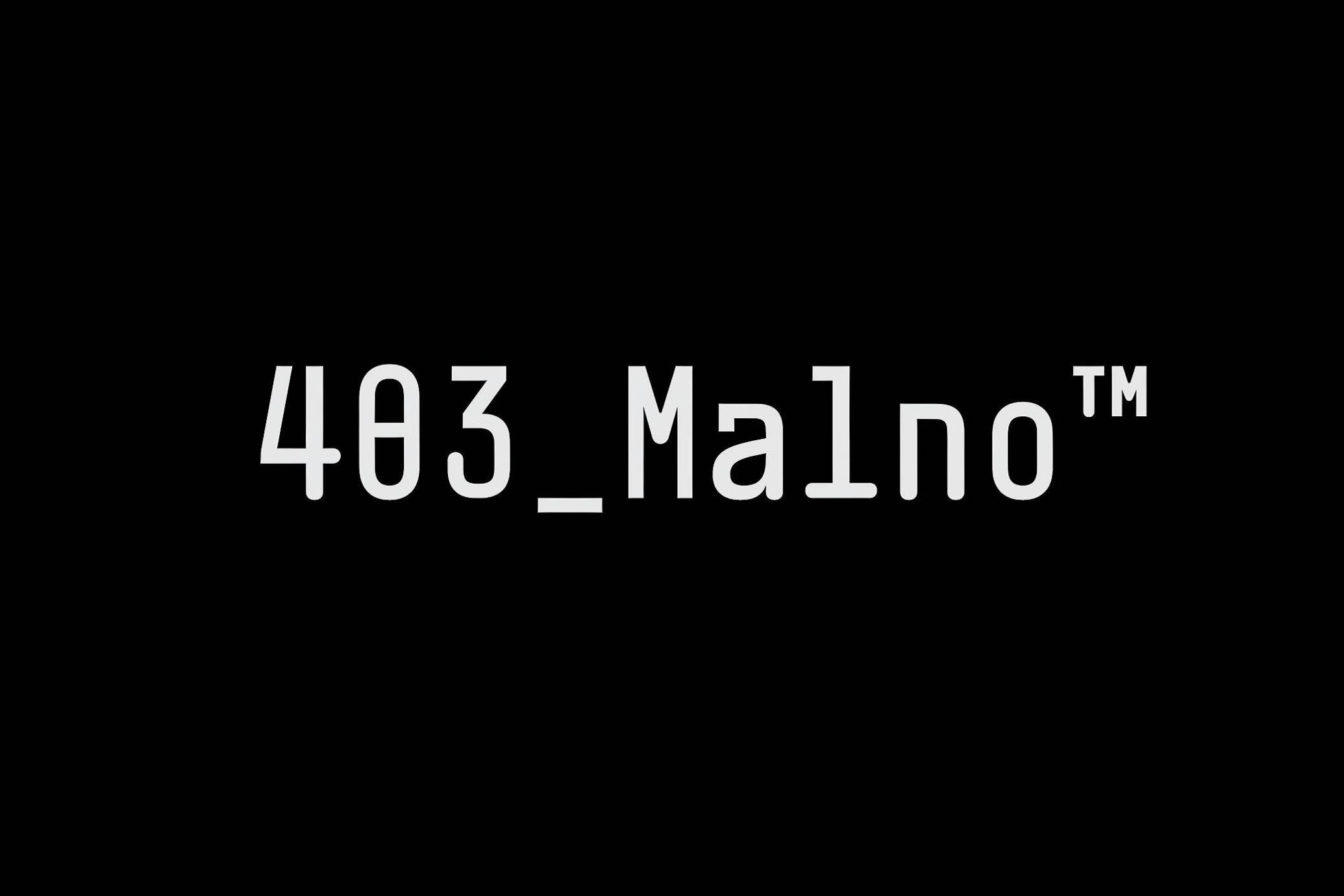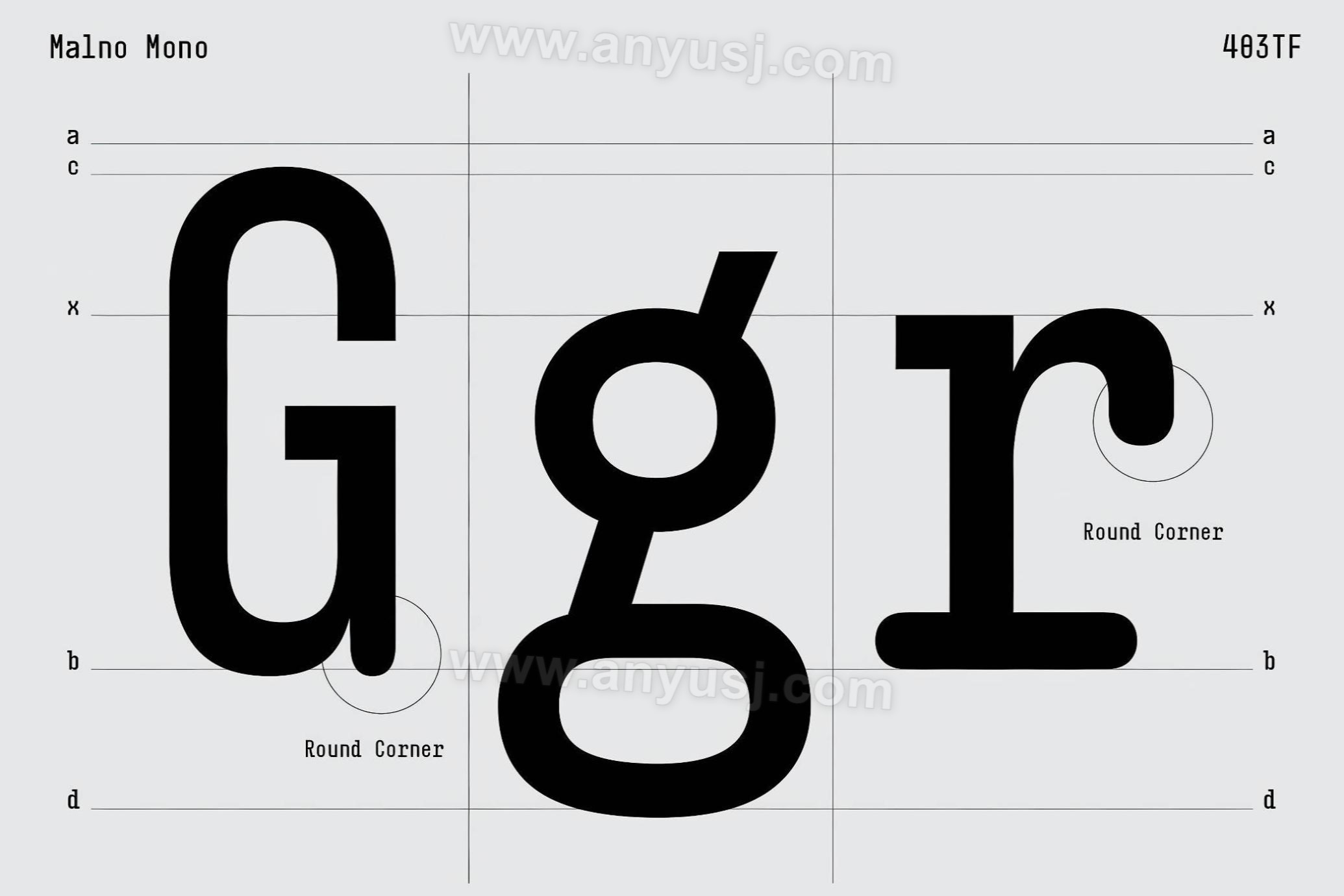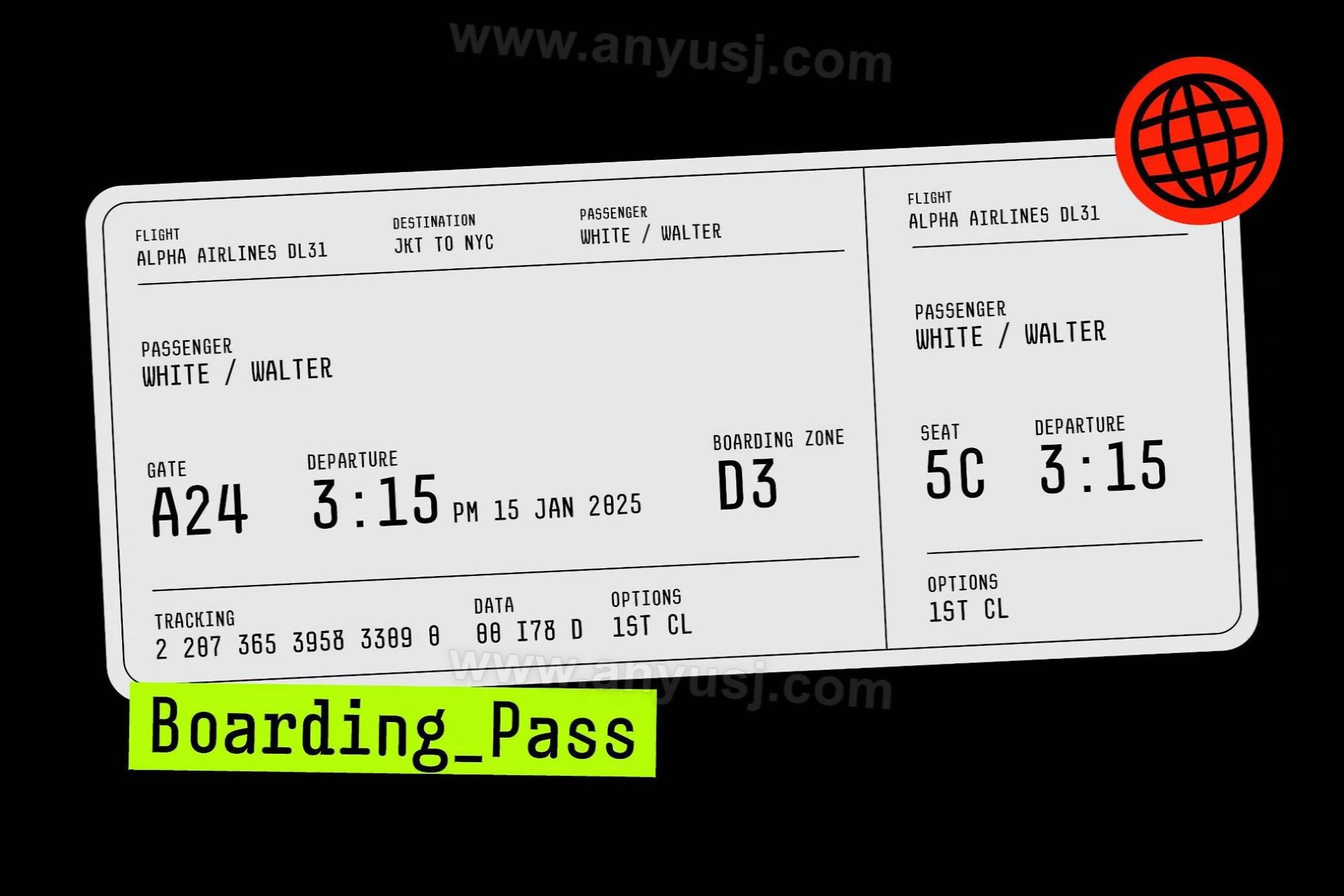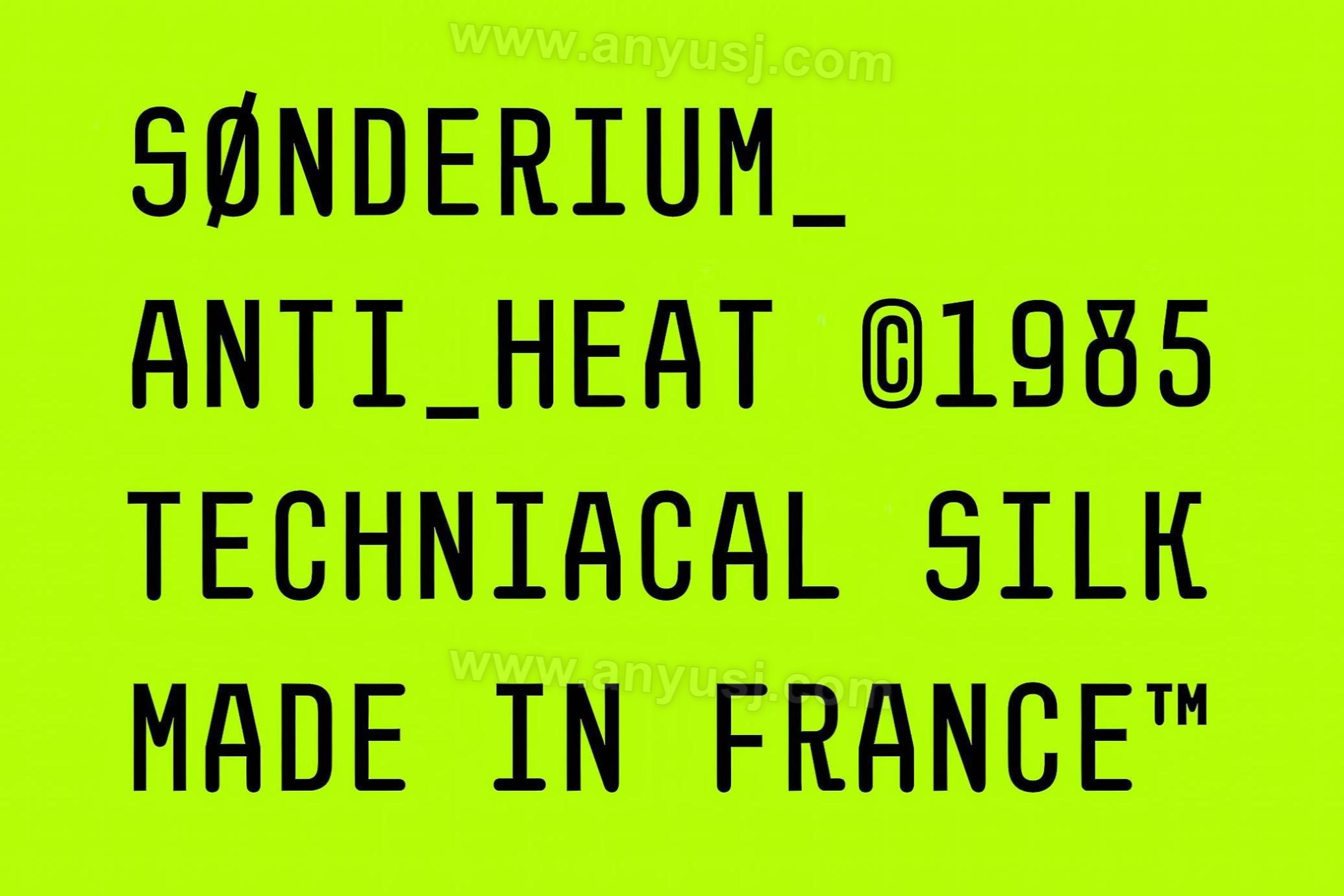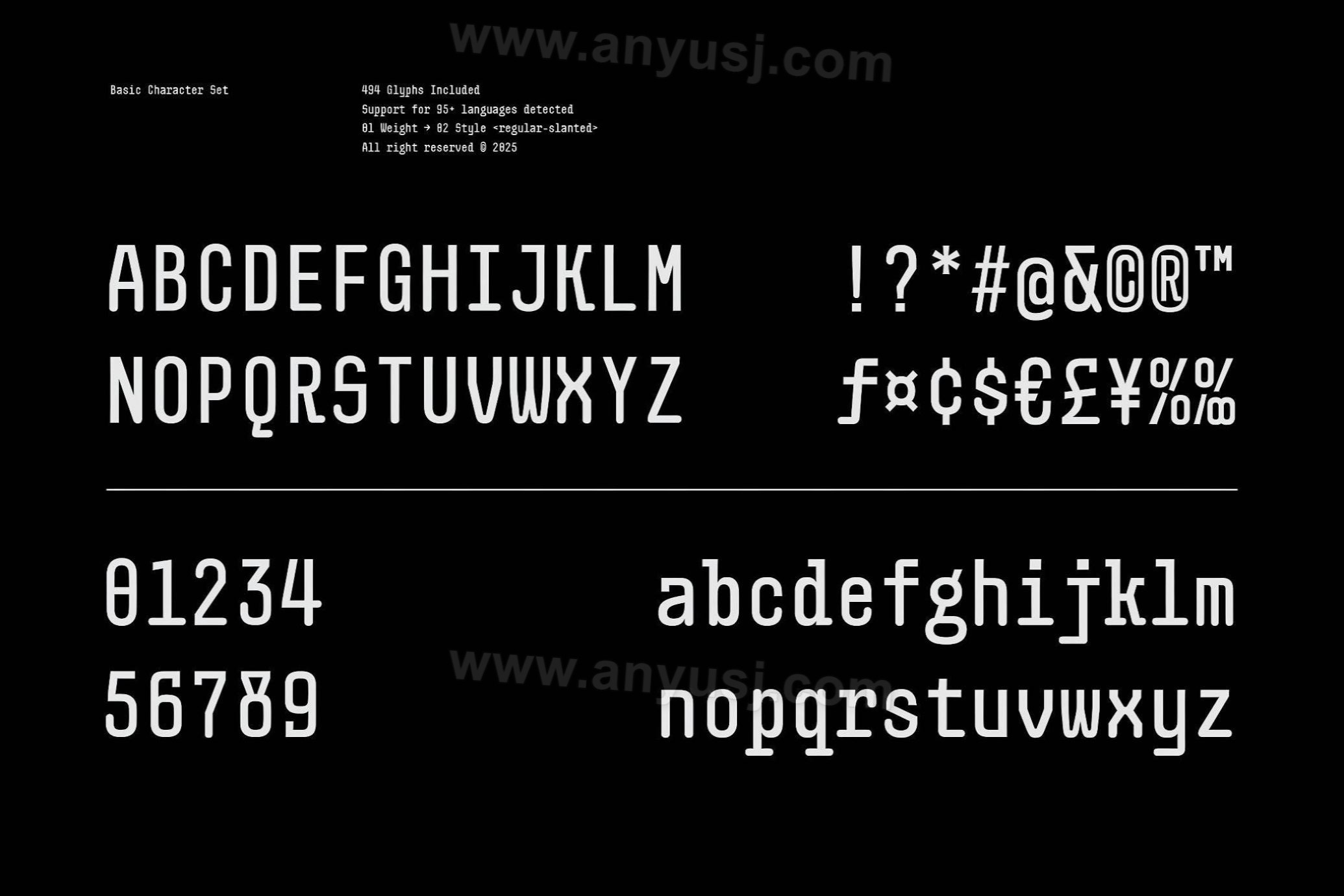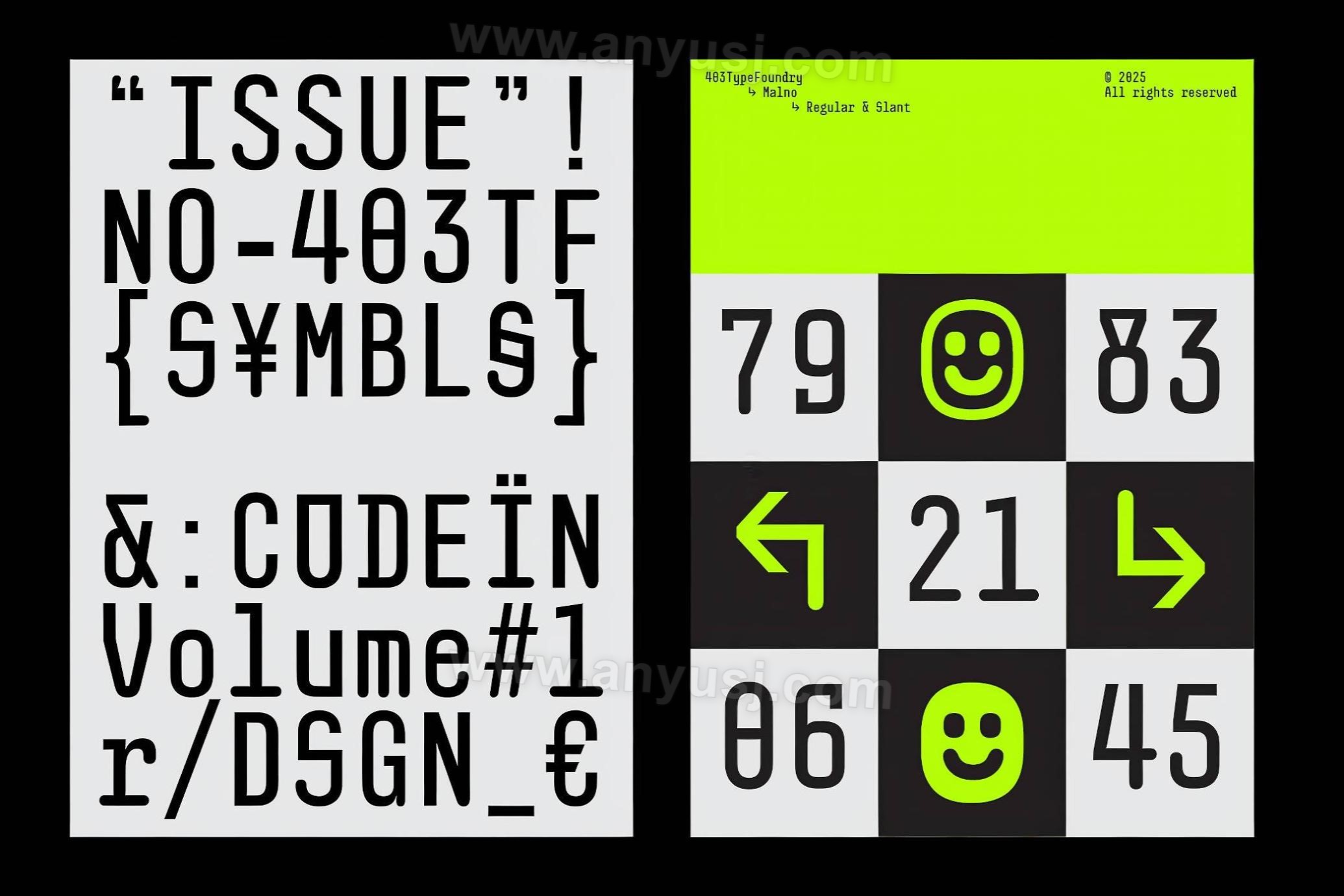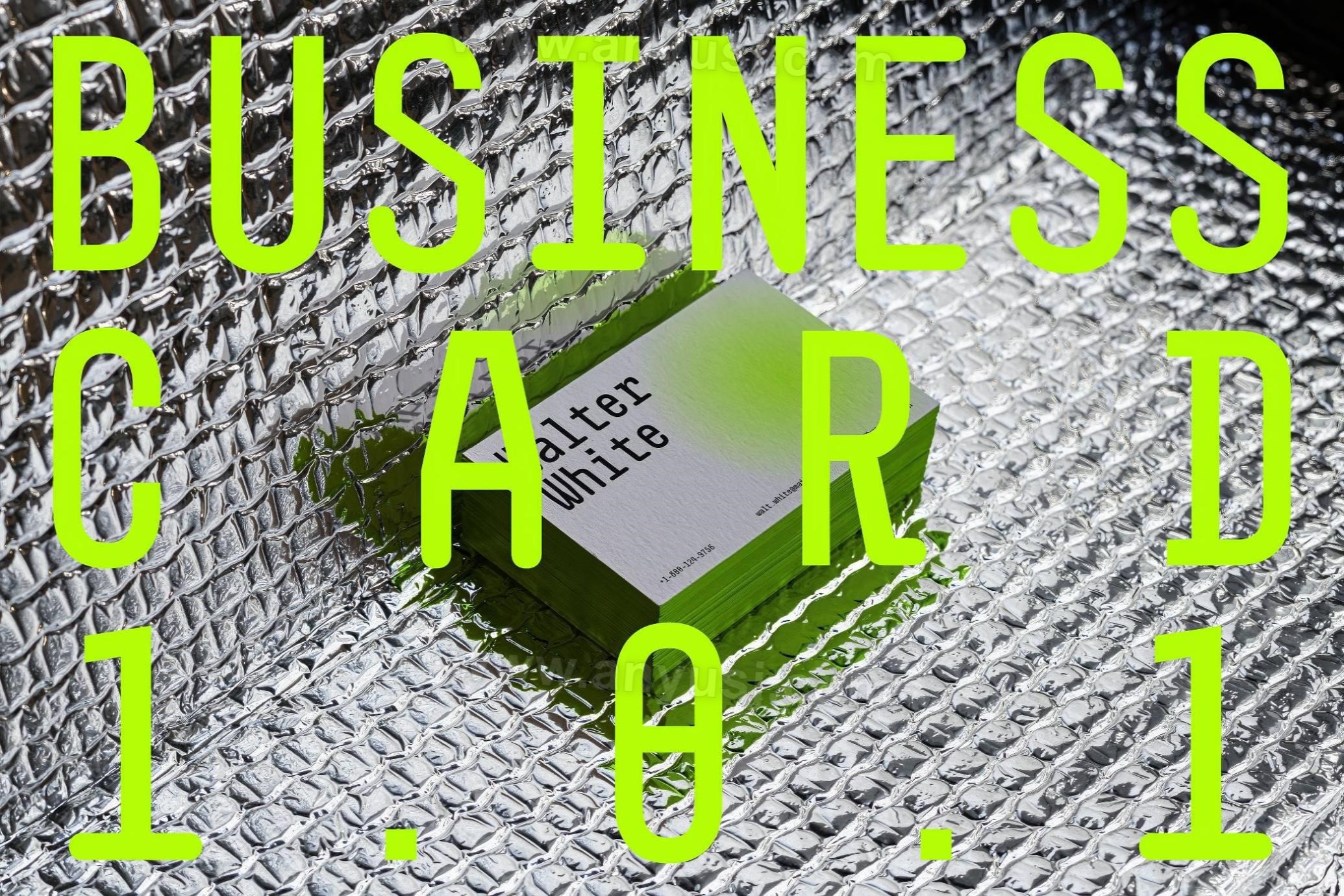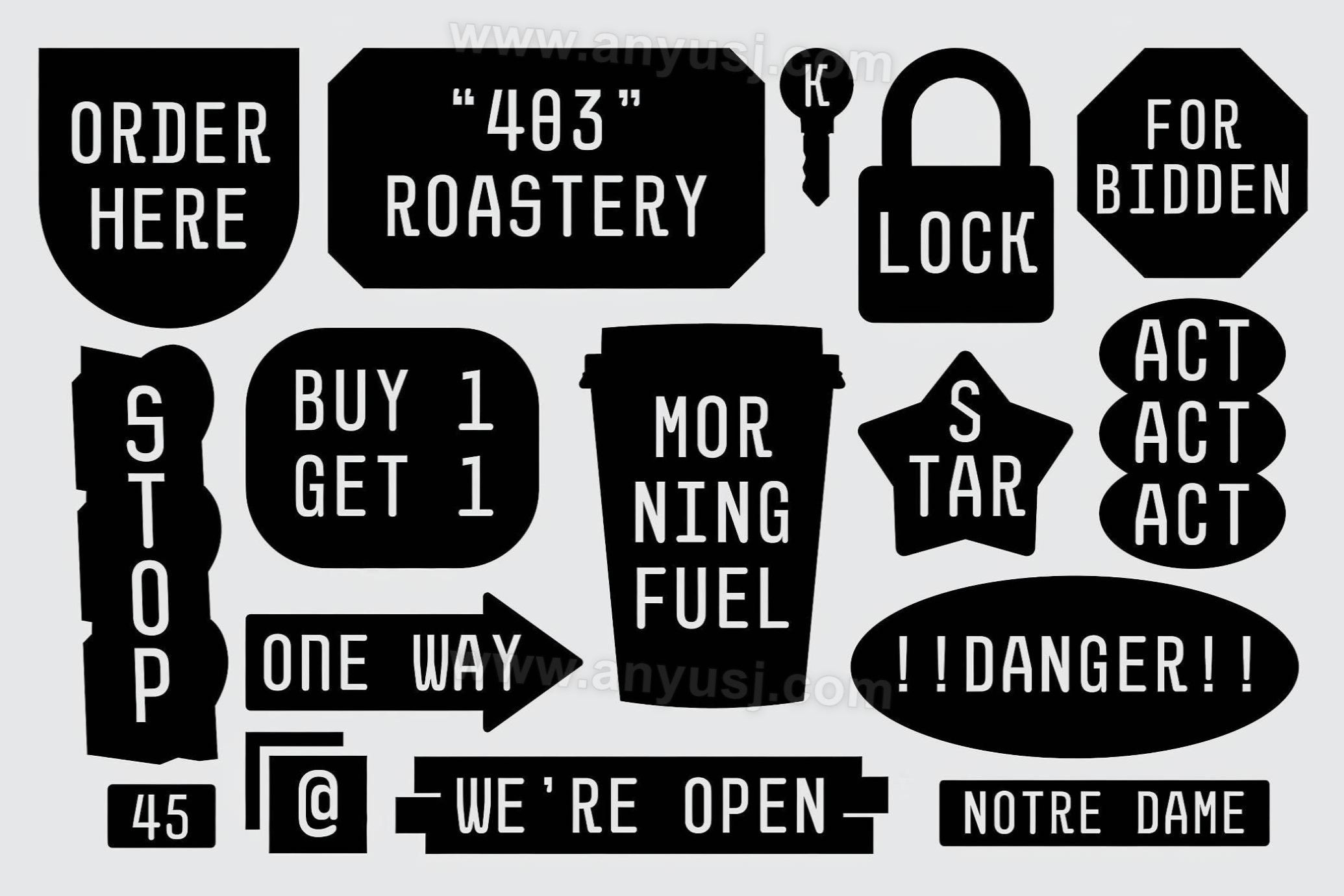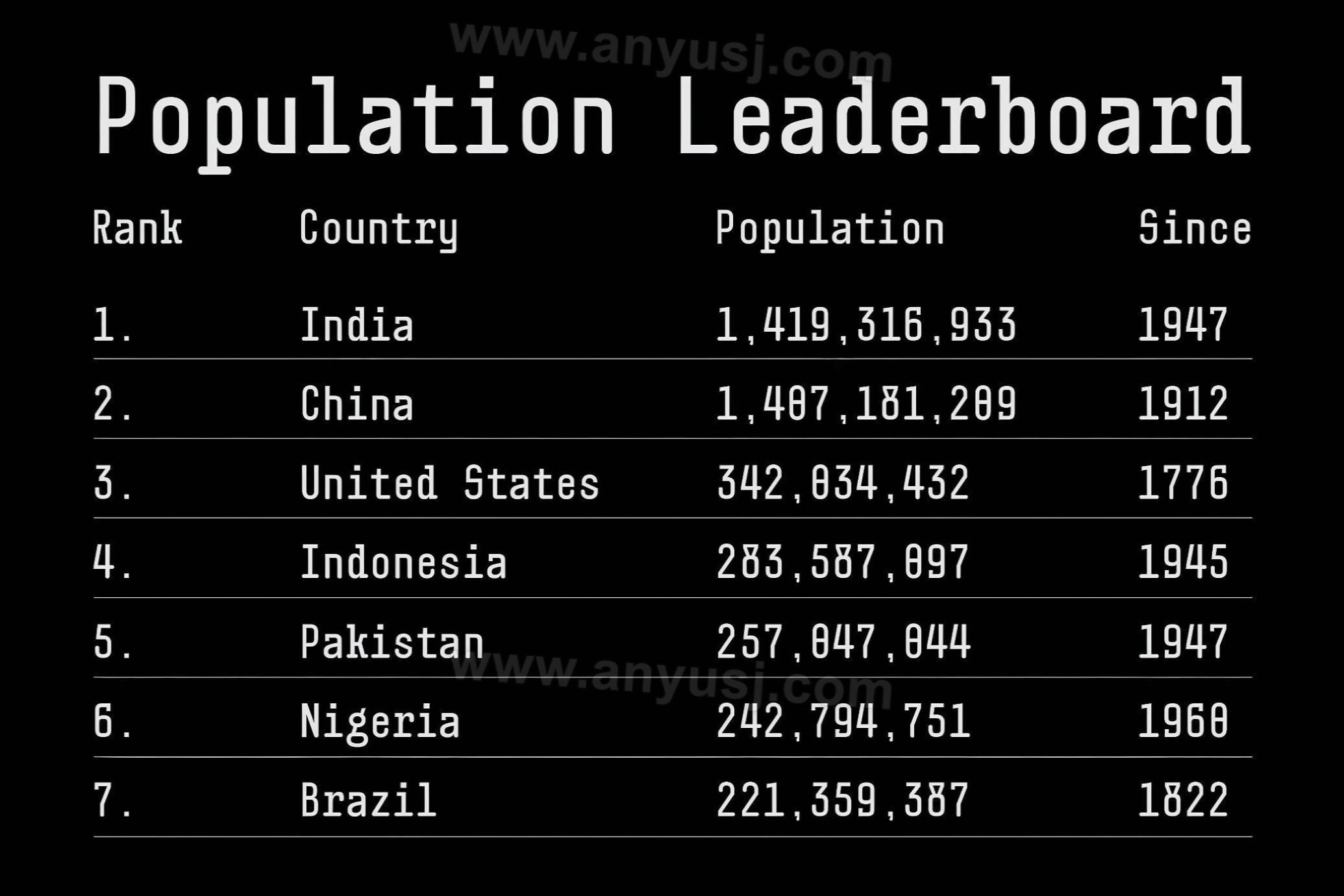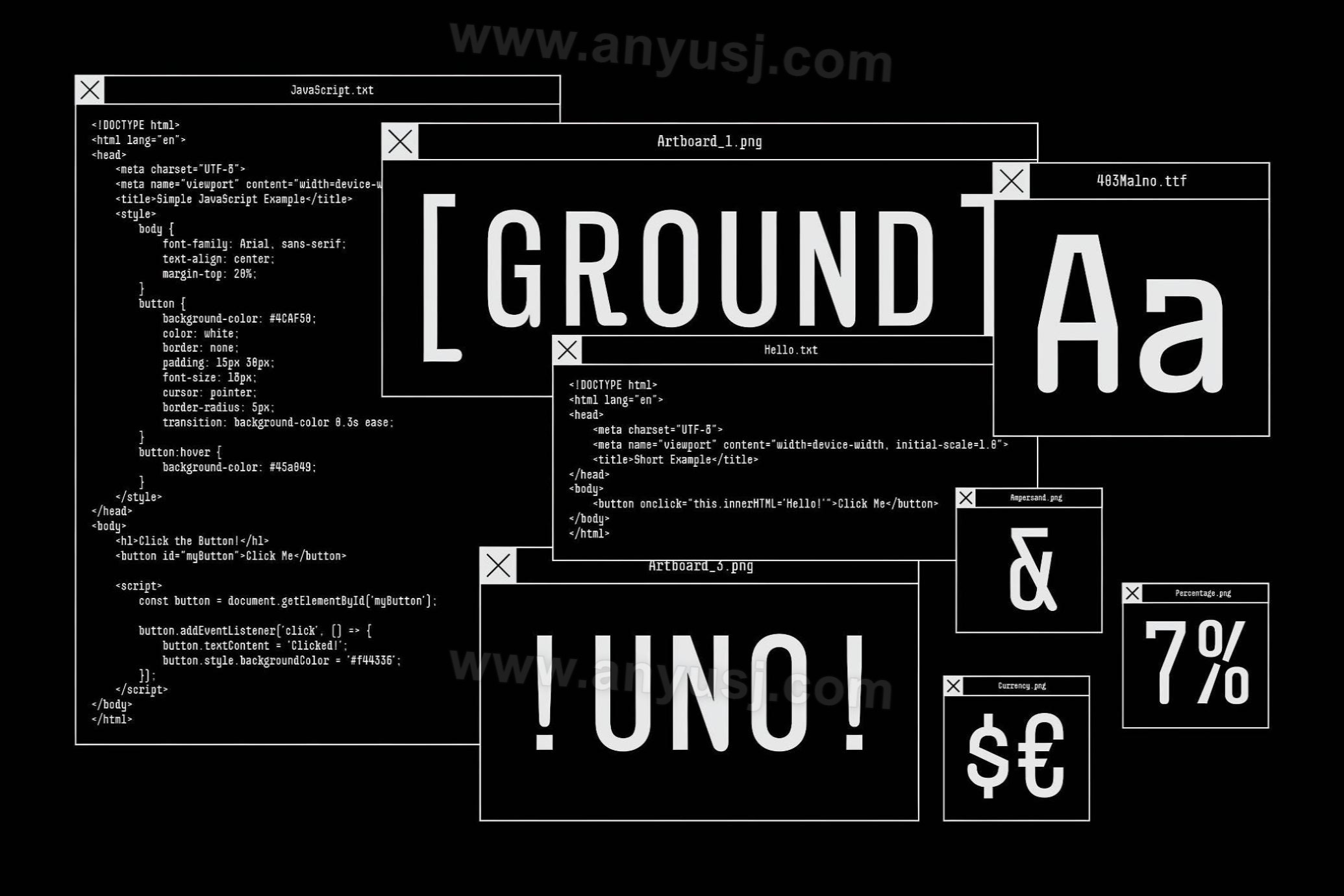
2款模块化数字等宽无衬线打印logo徽标英文西文字体403 Malno Mono — Sans Serif Font
如果 HAL 9000 曾经从事平面设计,这就是它会使用的字体。403 Malno 是一种模块化的等宽字体,具有外科手术般的精度和叛逆的气息——本质上是技术性的,但又有足够的古怪来让事情变得有趣。简洁的几何结构确保在密集的 UI 布局、终端屏幕或实验性编辑跨页中清晰易读,而不会丢失视觉识别。它配备 494 个字形并支持 95+ 种语言,专为广泛的覆盖范围和清晰的清晰度而构建。 两种样式(常规和倾斜)和一种精炼粗细以 OTF、TTF 和 WOFF 格式打包,使其成为数字和印刷项目的可靠资产。